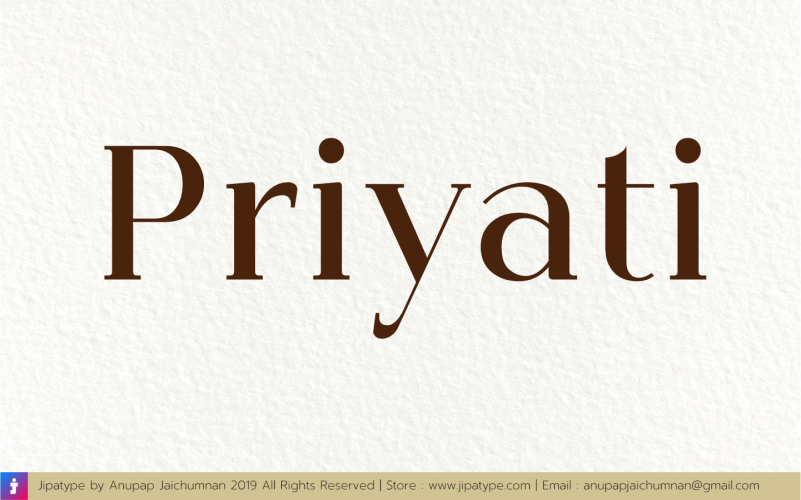
Priyati Serif Font – Fonte Grátis
Priyati Serif Font – Download Grátis
Priyati Serif Font
Aqui está uma breve e envolvente descrição para a página de download da font ‘Priyati Serif Font’, focada no tom informativo e convidativo: Nossa fonte ‘Priyati Serif’ é um deslumbrante recurso gráfico que oferece estilo e elegância em todos os projetos. Criada pelo designer talentoso Anupap Jai ChJPa, esta serif font é perfeita para escritas formais e textos profissionais. Com uma variedade de opções, a ‘Priyati Serif’ permite criar um texto atraente sem precisar usar cores ou ícones adicionais. Os usuários individuais podem usar gratuitamente esta fonte. Para usos comerciais, o designer oferece licenças e todo o conjunto completo da fonte através do link fornecido. Se você deseja contribuir para este projeto de qualidade, também tem a opção de fazer uma doação ao desenvolvedor. Agora é hora de dar vida à sua criação com ‘Priyati Serif’. Completamente customizable e fácil de integrar nos seus projetos digitais, esta fonte vai garantir que o seu texto seja sempre elegante e profissional. Não deixe de experimentar e ver como ela pode transformar suas próximas produções.